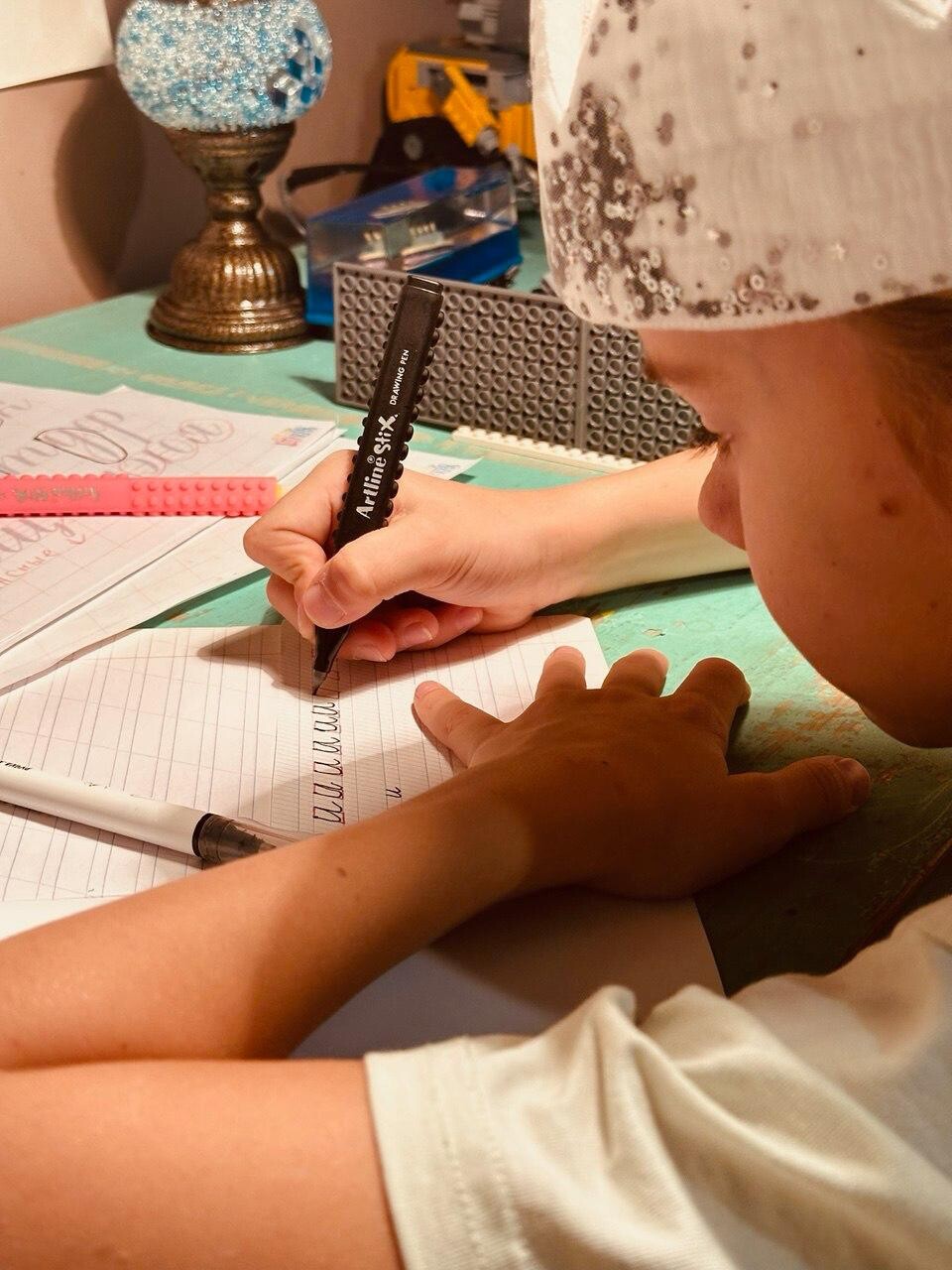
Многие из нас помнят это гнетущее чувство из детства: красная паста в тетради, размашистое «Старайся!» на полях и ощущение собственного бессилия. Мы видим, как современные дети замирают над чистым листом, их плечи поднимаются к ушам, пальцы белеют от сжатия ручки, а в глазах закипают слезы. В этот момент мы, взрослые, часто совершаем одну и ту же ошибку — призываем ребенка к аккуратности и усидчивости. Однако важно признать: письмо — это не морально-волевое качество. Это сложная психофизиологическая техника, которая сродни спорту или танцу.
Когда результат не радует, проблема почти никогда не заключается в лени или отсутствии старания. Напротив, дети часто прикладывают чрезмерные усилия, превращая письмо в изматывающую борьбу с собственным телом. Но правда в том, что «старание» не способно заменить отсутствие верного алгоритма движения.
Буква как след живого движения
Чтобы помочь ребенку, нам нужно изменить сам взгляд на то, что происходит на бумаге. Буква — это не статичная картинка, которую нужно скопировать или «срисовать». Это след, оставленный движением руки в пространстве. Если само движение изначально выстроено неверно, результат на бумаге неизбежно будет «сломанным».
Представьте спортсмена, который пытается пробежать марафон, не владея техникой шага, или пловца, совершающего хаотичные гребки. Сколько бы они ни старались, они лишь быстрее истощат свои силы. В письме всё работает точно так же. Здесь существует своя техника — вдох и выдох, правильный нажим, а главное — верное направление (вектор) движения.
Когда мы требуем от ребенка «писать красиво», мы фокусируемся на финальной точке. Но для легкости письма нужно сфокусироваться на пути. Если ребенок не понимает, откуда начинается движение, где находится центр буквы и куда должен быть направлен импульс, он вынужден каждый раз «изобретать» букву заново. Это колоссальная нагрузка на мозг, которая приводит к быстрому истощению ресурсов.
Овал — главный ключ к алфавиту
В основе нашей письменности лежит удивительная логика. Письмо — это конструктор, состоящий из ограниченного набора элементов. И самым важным, фундаментальным элементом здесь является овал.
Задумайтесь: овал составляет основу почти 60% букв русского алфавита. Это не просто буква «О». Это «а», «д», «б», «ю» и многие другие — всего 17 знаков, объединенных единой моторной логикой. Если ребенок осваивает правильное написание овала (строго против часовой стрелки), он автоматически получает ключ к половине алфавита. Ошибка в векторе движения делает соединения букв невозможными, письмо замедляется, а рука входит в состояние постоянного напряжения.
От напряжения — к ясности и ритму
Когда техника письма нарушена, ребенок держит не строку и не смысл текста, он держит напряжение. Вся его энергия уходит в зажатую ладонь и плечо. Мы же стремимся к тому, чтобы письмо стало «прозрачным» процессом, как дыхание.
Ясность техники дает ребенку самое главное — уверенность. Когда я знаю, как строится буква, когда я чувствую ритм движения, мне не нужно гадать. «Я могу» рождается из понимания алгоритма. Мы сначала ставим правильное движение, затем отрабатываем технику и только в самом конце переходим к объему.
Попытка нарастить объем письма (писать много страниц прописей), когда техника не сформирована — это путь к закреплению ошибок и отвращению к учебе. Мы идем иным путем: через расслабление руки и осознание каждого элемента. Мы учим ребенка чувствовать инструмент, будь то кисть или ручка, и понимать, что письмо может быть легким.
Фиксация понимания
Письмо — это навык, который требует времени и правильной последовательности шагов. Нам важно признать опыт ребенка: ему действительно бывает трудно не потому, что он «не старается», а потому, что его моторная система еще не получила верных инструкций.
Возвращаясь к основам — к правильному хвату и верному направлению овала, — мы даем ребенку опору. Мы переводим письмо из разряда «тяжелого труда» в разряд «понятной техники». Когда рука становится легкой, а траектория движения — привычной, освобождается место для творчества и живой мысли. Наша задача как взрослых — не требовать аккуратности, а обеспечить ребенку этот технический фундамент, на котором он сможет выстроить свой собственный путь в мир знаний, где письмо будет не препятствием, а надежным инструментом.